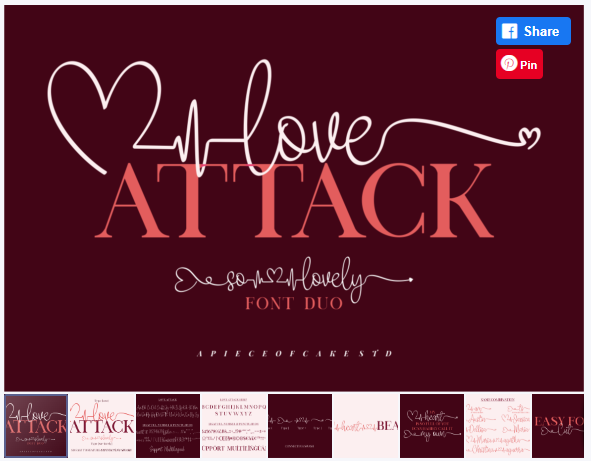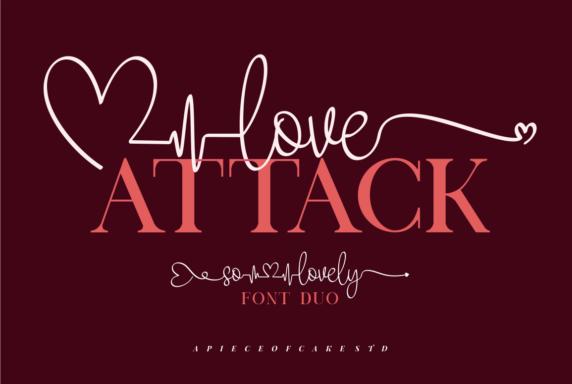
[Creativefabrica] Love Attack Font (a piece of cake)
Love Attack - это стильный и нежный рукописный дуэтный шрифт, подходящий для широкого спектра применений.